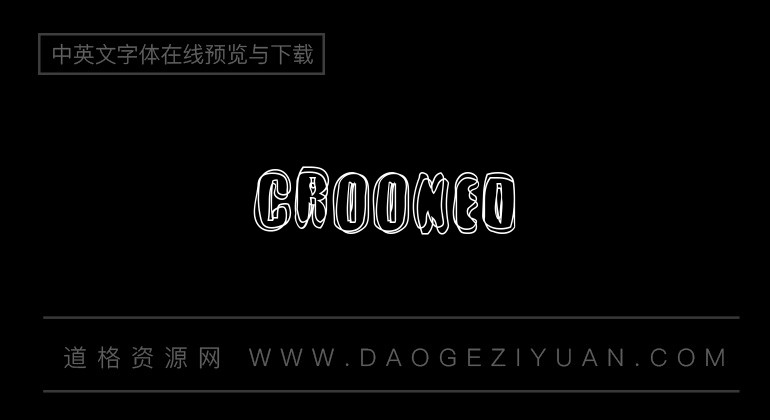
Crooked
? Crooked 字体是一款手写风格的字体,它具有流畅的线条和令人惊叹的细节,可以帮助您的设计看起来更具有活力和自然的感觉。它的特点是它的笔画更加曲折,更加柔和,而且它的字形设计也更加自然。Crooked 字体可以用于海报,标题,卡片,T恤,品牌标识等场景,可以给设计带来更多的创意灵感。
Crooked是一款非常不错的手写艺术字体,具有很好的视觉感,适合于文化类的宣传设计、商业类品牌的广告和产品包装设计以及个性化文字排版等较多场景。